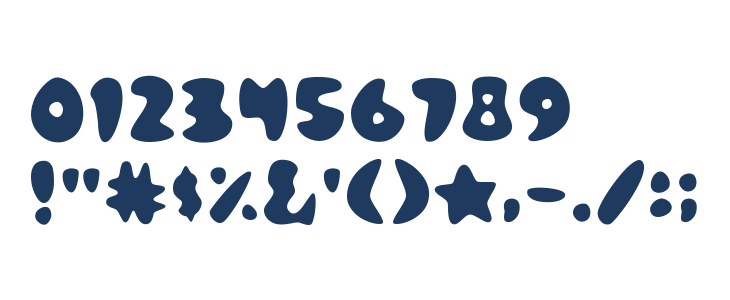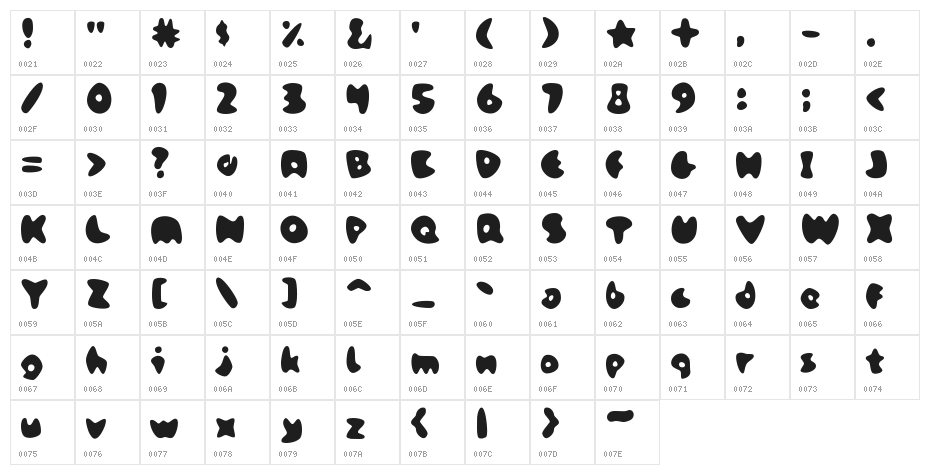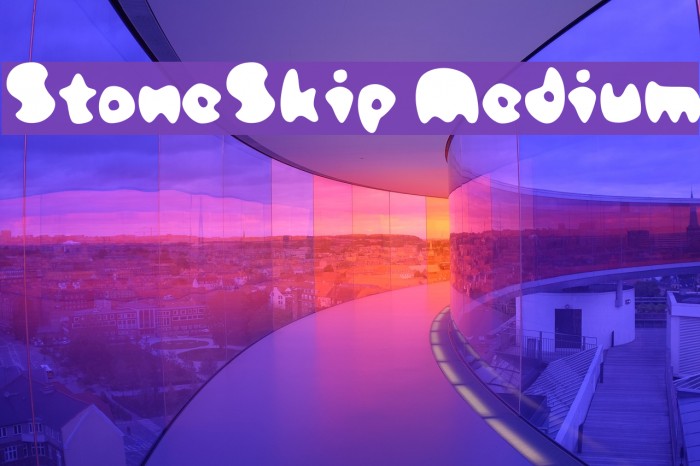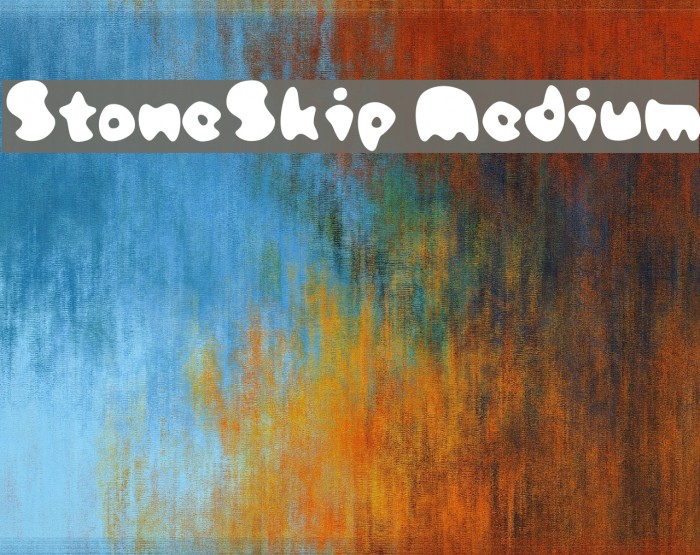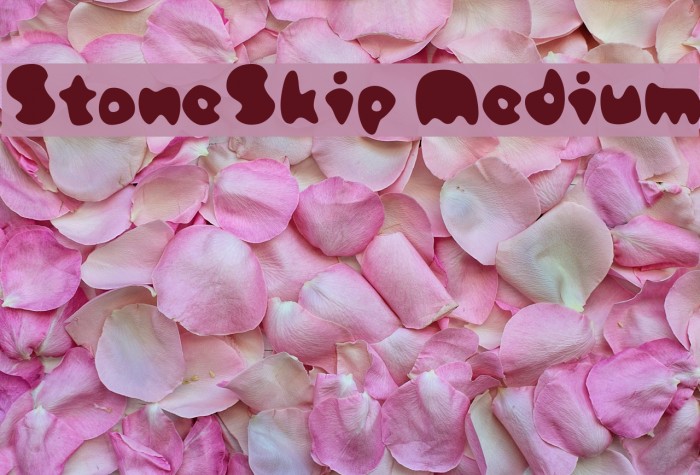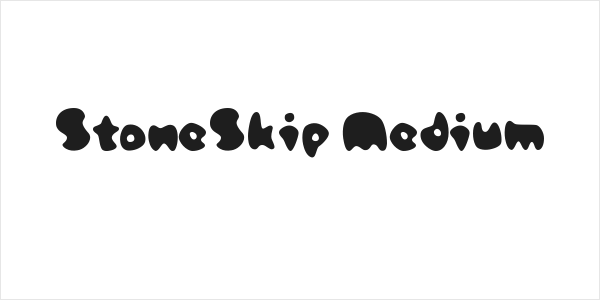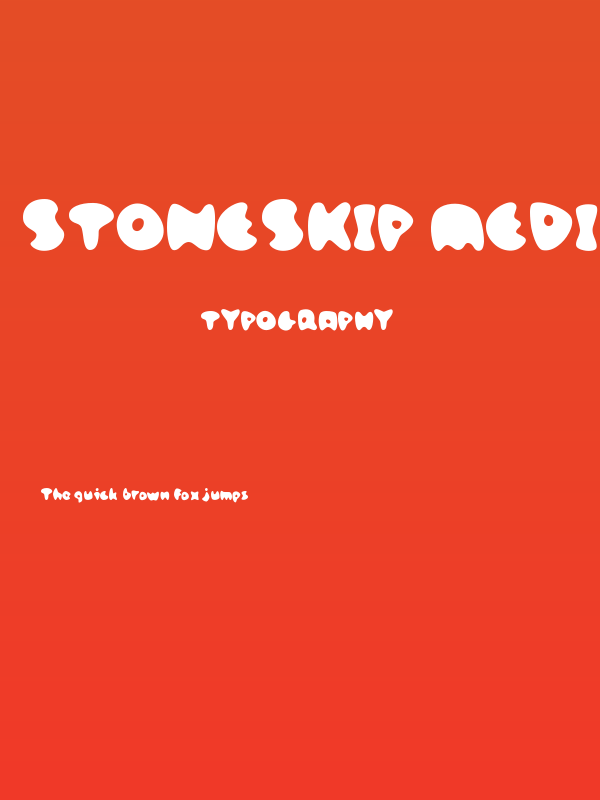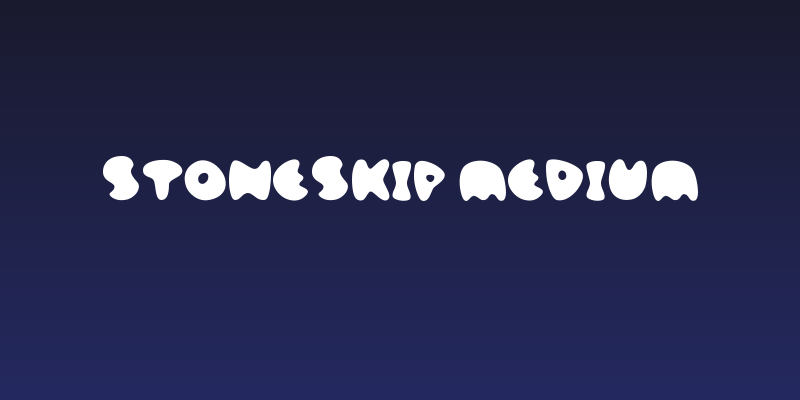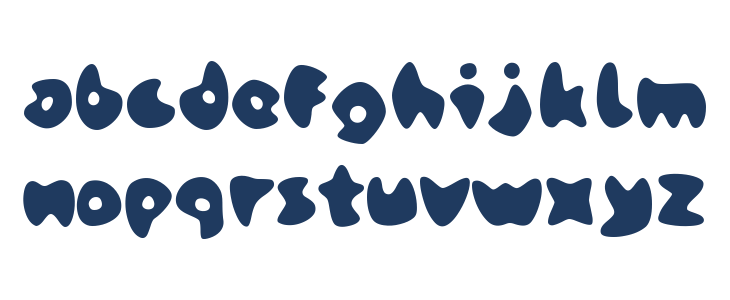
StoneSkip Medium Font
| Estilo general | Playful, Whimsical |
| Caso de uso | Logos, Posters, Children's Books |
| Proyectos propuestos | Ideal for children's books, playful branding, party invitations, and creative posters. |